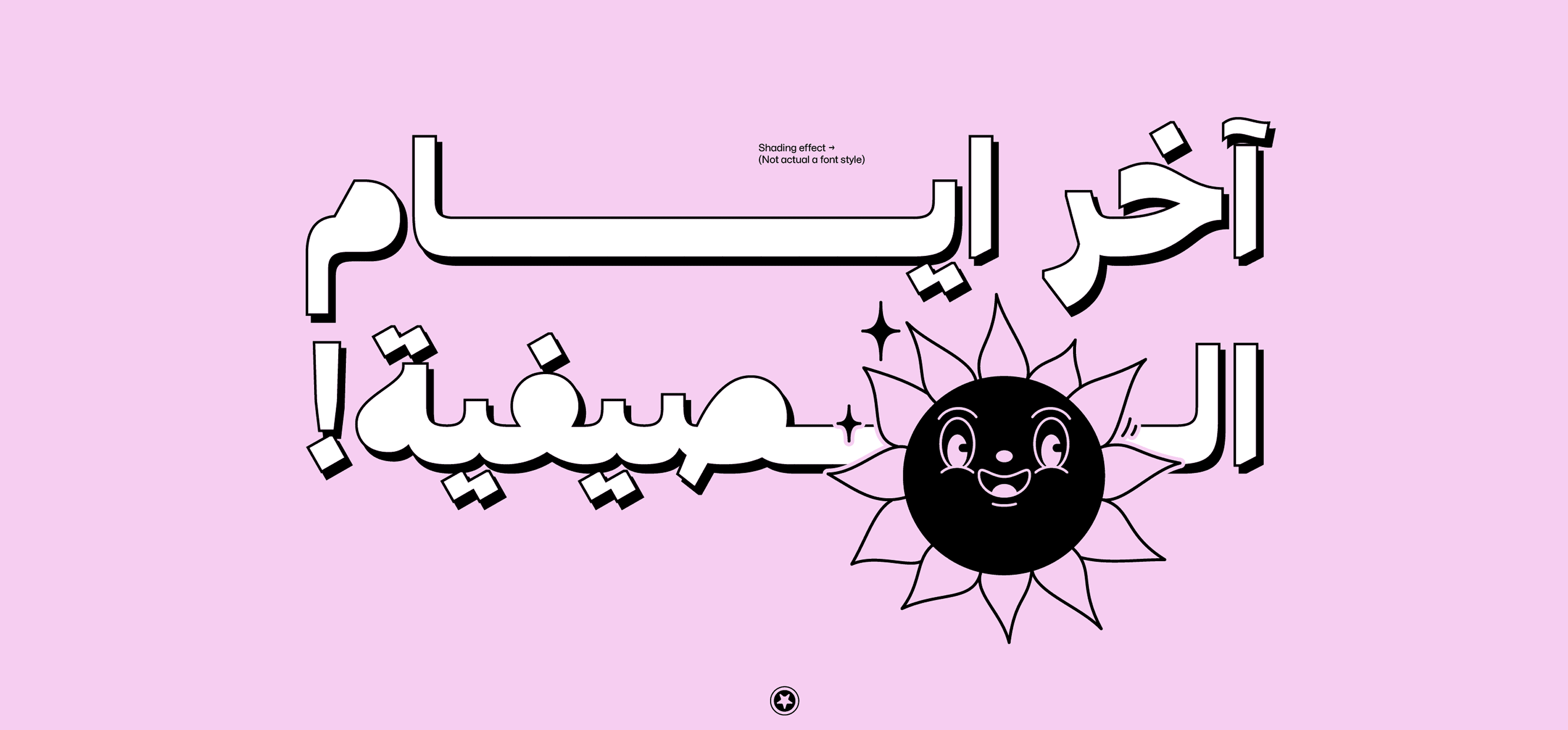
تعريف بخط "Zael" العربي الجديد:
"Zael" هو خط عرض عربي لافت للنظر، صُمم بقاعدة عريضة مستوحاة من الخط النسخي، مما يجعله جذّابًا بصريًا للشاشات والعناوين. يستلهم الخط من جماليات الخط النسخي الكلاسيكي، لكنه يدمج لمسات عصرية تجعله مناسبًا لتصاميم اليوم الحديثة. يُعد خيارًا مثاليًا لإنشاء ملصقات بصريّة مميزة ومتناسقة مع العلامات التجارية المعاصرة.